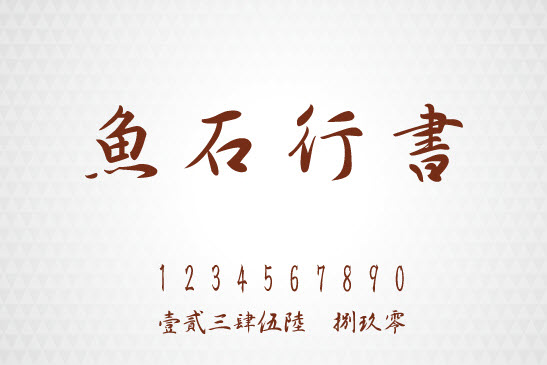
魚(yú)石行書(shū)
魚(yú)石行書(shū)字體是一款非常有個(gè)性的行書(shū)字體,筆法鋒利硬朗,非常的剛勁有力,寫(xiě)出的中文和繁體字,有一種濃厚的古風(fēng)氣息,歡迎喜愛(ài)的朋友到綠色資源網(wǎng)下載使用!
魚(yú)石行書(shū)字體是小編一直以來(lái)都蠻喜歡一個(gè)非常好看的書(shū)法字體,話說(shuō)小學(xué)時(shí)練毛筆字,初練是可是吃了不少苦頭,不過(guò)后來(lái)還是很行的哦,咳咳,扯遠(yuǎn)了,我們現(xiàn)在推薦這款電腦上使用的字體給大家使用,不過(guò)需要注意魚(yú)石行書(shū)只支持繁體中文哦!